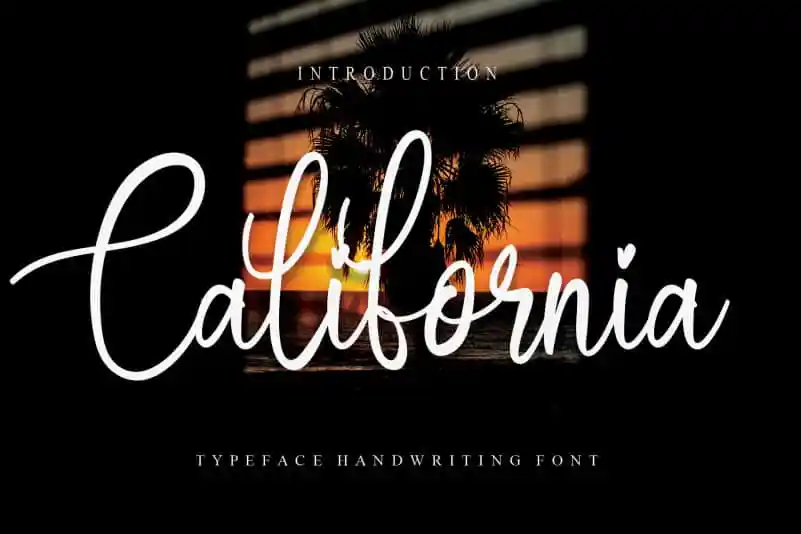
California Script Font – Download Grátis
Aqui está uma descrição em português para a página de download da fonte ‘California Script Font’, mantendo o tom informativo e convidativo: Embrenhada na essência da cultura brasileira, a California Script Font carrega um toque suave e elegante, combinando perfeitamente com textos criativos. Desenhada por um talentoso designer chamado creativeletter, essa fonte transmite um ar de sofisticação que se alinha perfeitamente com o estilo do seu trabalho. Com traços sutis e harmoniosos, ela é ideal para criações artísticas e personalizadas, proporcionando uma experiência única para quem a utiliza. Perfeita tanto para design gráfico profissional quanto para expressar sentimentos pessoais em postagens no Instagram ou outros canais digitais, a California Script Font oferece o toque autêntico que sua peça de trabalho merece.